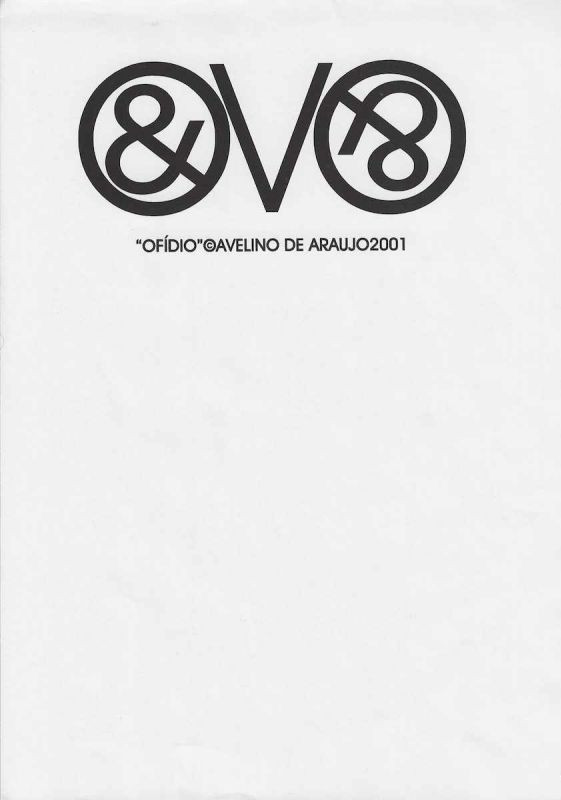
Ofídio é uma impressão gráfica de Avelino de Araújo realizada em 2001, vinculada à poesia visual, à poesia experimental, à arte conceitual, à tipografia e às investigações intersígnicas relacionadas ao campo do Poema Processo.
Avelino de Araújo
Categoria: Poema Processo
Data: 2001
Ofídio é uma impressão gráfica de Avelino de Araújo realizada em 2001, vinculada à poesia visual, à poesia experimental, à arte conceitual, à tipografia e às investigações intersígnicas relacionadas ao campo do Poema Processo. A composição apresenta dois grandes círculos pretos posicionados simetricamente nas extremidades de uma estrutura central semelhante à letra V. Dentro de cada círculo aparece uma forma tipográfica próxima ao sinal &, submetida a diferentes rotações e orientações. A organização visual transforma letras e sinais gráficos em uma figura que pode ser associada a uma serpente enrolada, a dois organismos circulares, a olhos ou a emblemas espelhados. O título Ofídio designa os répteis do grupo das serpentes e orienta a interpretação das linhas curvas, dos enrolamentos e das formas fechadas presentes na imagem. O sinal & possui curvas que lembram o movimento de um corpo serpentino dobrado sobre si mesmo. Sua inserção dentro de círculos reforça ideias de enrolamento, ciclo, proteção, aprisionamento, repetição e movimento contínuo. A estrutura central em forma de V estabelece uma separação e simultaneamente uma ligação entre os dois módulos laterais. Essa forma pode ser compreendida como eixo de simetria, bifurcação, língua de serpente, abertura, passagem ou sinal gráfico intermediário. A obra explora as relações entre organismo e alfabeto, figura animal e código tipográfico, leitura e reconhecimento visual. Os dois módulos apresentam semelhanças estruturais, mas diferem na orientação interna do sinal, criando um efeito de espelhamento e reversão. Avelino de Araújo transforma o caractere tipográfico em matéria plástica e constrói uma imagem ambígua que pode ser lida como palavra, símbolo, animal, máscara ou diagrama. O forte contraste entre preto e fundo claro produz leitura imediata e destaca a economia formal da composição. O amplo espaço vazio ao redor concentra a atenção sobre os três elementos principais e reforça sua aparência de signo isolado. Na parte inferior aparecem o título OFÍDIO, a marca de autoria, o nome Avelino de Araújo e o ano 2001. Ofídio integra a produção do artista baseada na apropriação de letras, sinais, formas geométricas e ambiguidades visuais como instrumentos de construção poética e reflexão sobre linguagem, natureza e percepção. Palavras chave para indexação: Avelino de Araújo, Ofídio, Ofidio, 2001, impressão gráfica, poesia visual brasileira, poema visual, poesia experimental, arte conceitual, Poema Processo, serpente, cobra, réptil, sinal tipográfico, ampersand, símbolo &, tipografia experimental, espelhamento, simetria, rotação, linguagem visual, figura animal, semiótica, intersigno, texto imagem, comunicação visual, arte gráfica brasileira, múltiplo gráfico, arquivo de poesia visual, arte brasileira do século vinte e um.TEXT FOR THE SALSA PROGRAM IN ENGLISH: Ophidian is a graphic print by Avelino de Araújo produced in 2001 and associated with visual poetry, experimental poetry, conceptual art, typography and intersemiotic investigations related to the field of the Poema Processo movement. The composition presents two large black circles positioned symmetrically on either side of a central structure resembling the letter V. Inside each circle appears a typographic form close to the ampersand sign, subjected to different rotations and orientations. The visual arrangement transforms letters and graphic signs into a figure that may be associated with a coiled serpent, two circular organisms, eyes or mirrored emblems. The title Ophidian refers to reptiles belonging to the group of snakes and guides the interpretation of the curved lines, coils and enclosed forms present in the image. The ampersand contains curves that resemble the movement of a serpentine body folded around itself. Its placement inside circles reinforces ideas of coiling, cycles, protection, confinement, repetition and continuous movement. The central V shaped structure creates a separation and at the same time a connection between the two lateral modules. This form may be understood as an axis of symmetry, bifurcation, serpent tongue, opening, passage or intermediate graphic sign. The work explores relationships between organism and alphabet, animal figure and typographic code, reading and visual recognition. The two modules share similar structures but differ in the orientation of the internal sign, creating an effect of mirroring and reversal. Avelino de Araújo transforms the typographic character into visual matter and constructs an ambiguous image that may be read as a word, symbol, animal, mask or diagram. The strong contrast between black and the light background produces immediate recognition and highlights the formal economy of the composition. The broad empty space around the image focuses attention on the three principal elements and reinforces their appearance as isolated signs. The lower section contains the title OFÍDIO, the authorship mark, the name Avelino de Araújo and the year 2001. Ophidian belongs to the artist production based on the appropriation of letters, signs, geometric forms and visual ambiguities as instruments of poetic construction and reflection on language, nature and perception. Keywords for indexing: Avelino de Araújo, Ophidian, Ofídio, Ofidio, 2001, graphic print, Brazilian visual poetry, visual poem, experimental poetry, conceptual art, Poema Processo, serpent, snake, reptile, typographic sign, ampersand, symbol &, experimental typography, mirroring, symmetry, rotation, visual language, animal figure, semiotics, intersign, text image, visual communication, Brazilian graphic art, graphic multiple, visual poetry archive, twenty first century Brazilian art.
Impressão gráfica em tinta preta sobre papel claro, composta por dois módulos circulares simétricos e uma grande forma central semelhante à letra V. Cada módulo lateral possui um círculo externo espesso e uma forma interna próxima ao sinal &, apresentada em orientação diferente. O módulo esquerdo contém o sinal em posição próxima à leitura convencional, enquanto o módulo direito apresenta uma configuração rotacionada ou invertida. O conjunto cria equilíbrio bilateral, forte contraste e associação visual com serpentes enroladas. A forma central é constituída por duas hastes diagonais que convergem em uma ponta inferior, funcionando como separação e ligação entre os círculos. A composição ocupa a região superior da folha e deixa uma extensa área branca nas regiões central e inferior. Abaixo da imagem aparece a inscrição OFÍDIO, seguida pelo símbolo de autoria, pelo nome Avelino de Araújo e pelo ano 2001. O suporte apresenta discretas ondulações, pequenos vincos e sinais leves de manuseio. A peça pode ser classificada como poema visual, impressão de artista, múltiplo gráfico, estudo tipográfico e documento conceitual, sendo relevante para pesquisas sobre Avelino de Araújo, Poema Processo, poesia visual, serpentes na arte, tipografia, simetria, semiótica, percepção e produção gráfica brasileira.OBSERVATION TEXT IN ENGLISH: Graphic print in black ink on light colored paper composed of two symmetrical circular modules and a large central form resembling the letter V. Each lateral module has a thick external circle and an internal form close to the ampersand sign, presented in a different orientation. The left module contains the sign in a position close to conventional reading, while the right module presents a rotated or inverted configuration. The composition creates bilateral balance, strong contrast and a visual association with coiled snakes. The central form consists of two diagonal strokes converging at a lower point and functions as both separation and connection between the circles. The image occupies the upper region of the sheet and leaves an extensive white area in the central and lower sections. Below the image appears the inscription OFÍDIO, followed by the authorship symbol, the name Avelino de Araújo and the year 2001. The support presents slight undulations, small creases and minor traces of handling. The piece may be classified as a visual poem, artist print, graphic multiple, typographic study and conceptual document, making it relevant to research on Avelino de Araújo, Poema Processo, visual poetry, snakes in art, typography, symmetry, semiotics, perception and Brazilian graphic production.
Ophidian is a graphic print by Avelino de Araújo produced in 2001 and associated with visual poetry, experimental poetry, conceptual art, typography and intersemiotic investigations related to the field of the Poema Processo movement.